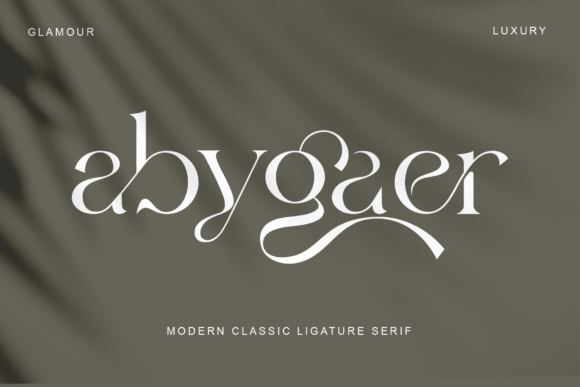
Creativefabrica Abygaer Font 2021
[Creativefabrica] Abygaer Font (2021)
Abygaer - это волнистый, шикарный и роскошный шрифт с засечками.
Abygaer характеризуется плавными изгибами и идеально подходит для модного брендинга или редакционного дизайна.